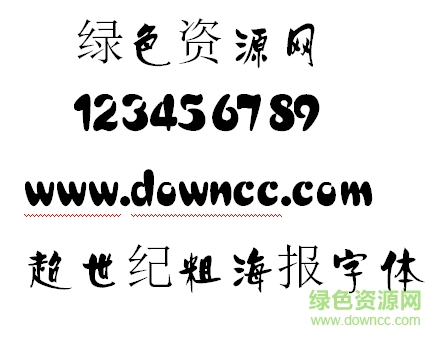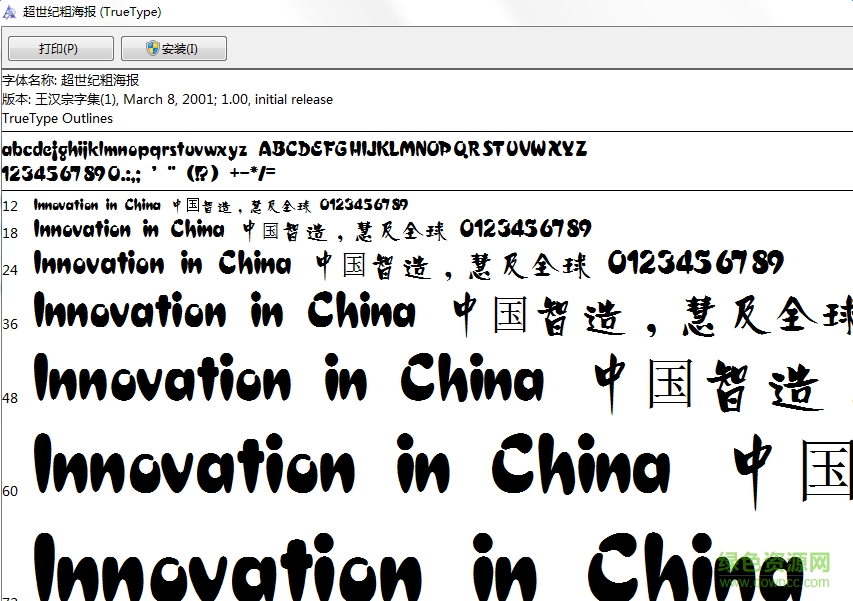
超世紀粗海報字體是一款超世紀字體官方打造的粗海報字體哦,專門為需要設(shè)計的用戶打造的海報字體,這款字體看上去十分具有藝術(shù)氣息,喜歡就來下載體驗唄!
超世紀粗海報字體是一款應(yīng)用于設(shè)計方面的中文簡體字體,外形漂亮大方,字形瀟灑,可以應(yīng)用于藝術(shù)設(shè)計、產(chǎn)品包裝、平面廣告等行業(yè)領(lǐng)域,喜歡的用戶可下載收藏。